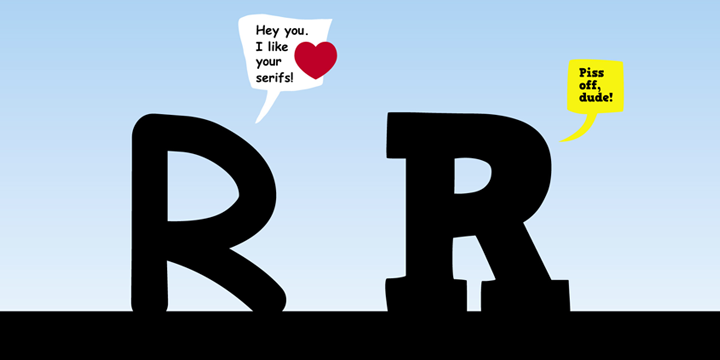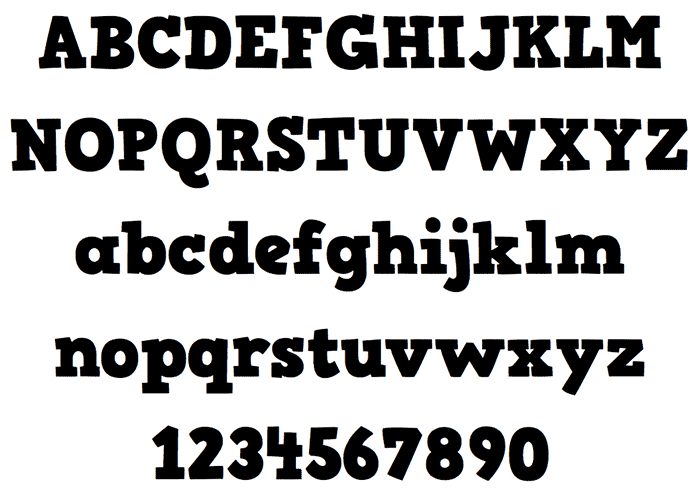
Comic Serif Pro 1.0
Eine Comic-Sans-Alternative mit Slab-Serifen von Hannes von Döhren. In den 438 Glyphen steckt eine west, ost- und zentraleuropäische Belegung.
Hannes von Döhren
This is a great offer, for example for the front page title of a comic book. On the inside of a present project, we are preparing to use Comic Neue for speech balloons. But that is somewhat too tame to make a catchy title. So when I discovered Comic Serif Pro, it made me glad. Good work and thank you for making this a free download.